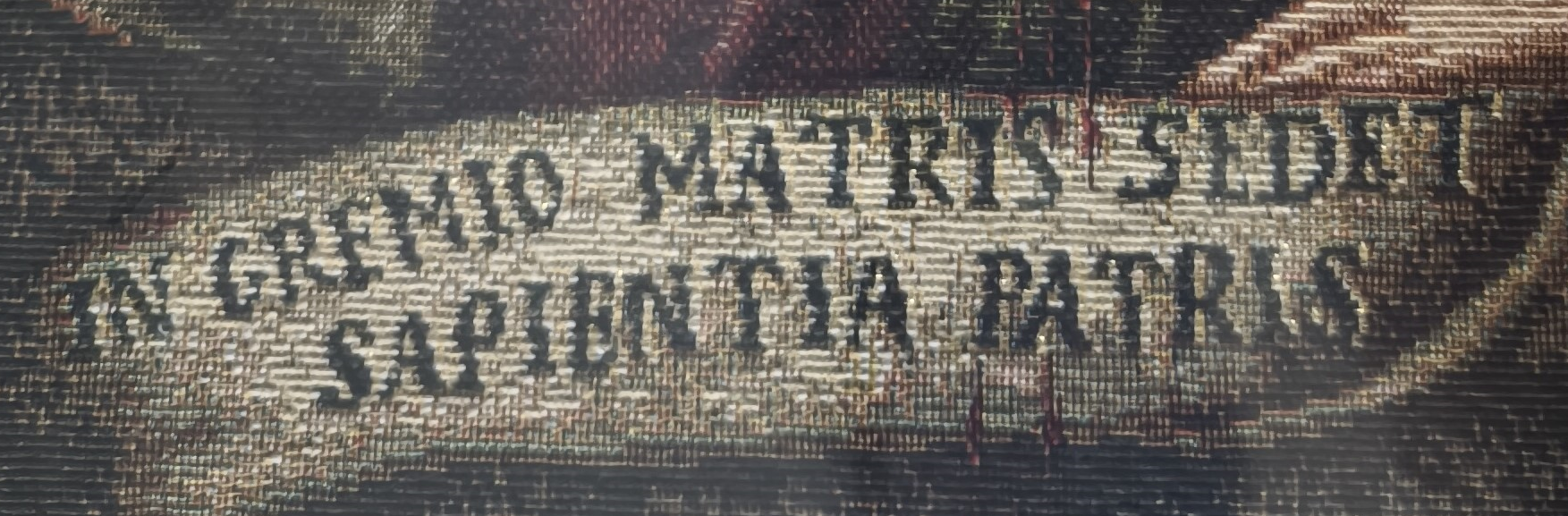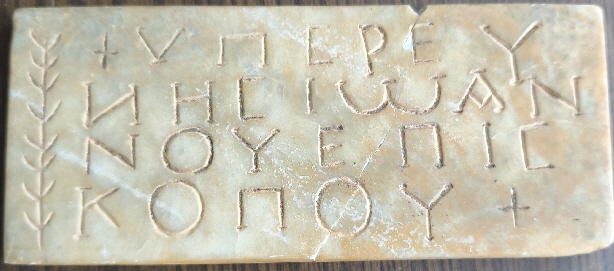
In unserer Ausstellung sehen Sie Zeugnisse der Schreibkultur aus über 5000 Jahren. Von der Keilschrift der Sumerer bis zu modernen Schriftsystemen. Staunen Sie über die Vielfalt der Schriften der Welt.
Europa
Griechisch, Lateinisch und Kyrillisch
Asien
Chinesisch, Japanisch, Mongolisch, Devanagari, Tibetisch, Hebräisch, Arabisch — und als Besonderheit die Gongchepu-Notation
Alte Schriften
Ägyptische Hieroglyphen und Keilschrift
Deutschland
Runen, karolingische Minuskeln, Fraktur, Kurrentschrift, Sütterlinschrift bis zur Schulausgangsschrift und der Grundschrift
Amerika
Inka, Azteken und Maya
Zahlen & Noten
Europäische Notation und klassische japanische Notation
Schreibgeräte
Vom Holzstab über die Gänsefeder, Stahlfedern, Füllfederhalter, Kugelschreiber, Tintenroller und Filzstifte
Konservierung
Kann man in 100 Jahren noch lesen, was wir heute schreiben?